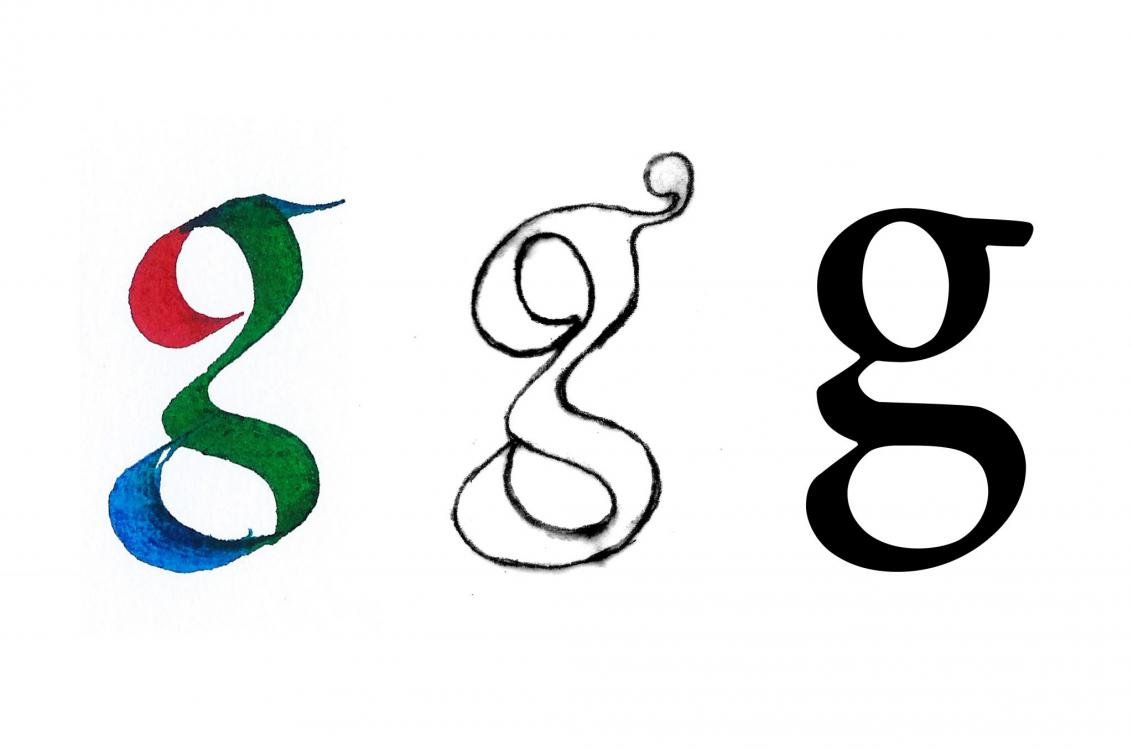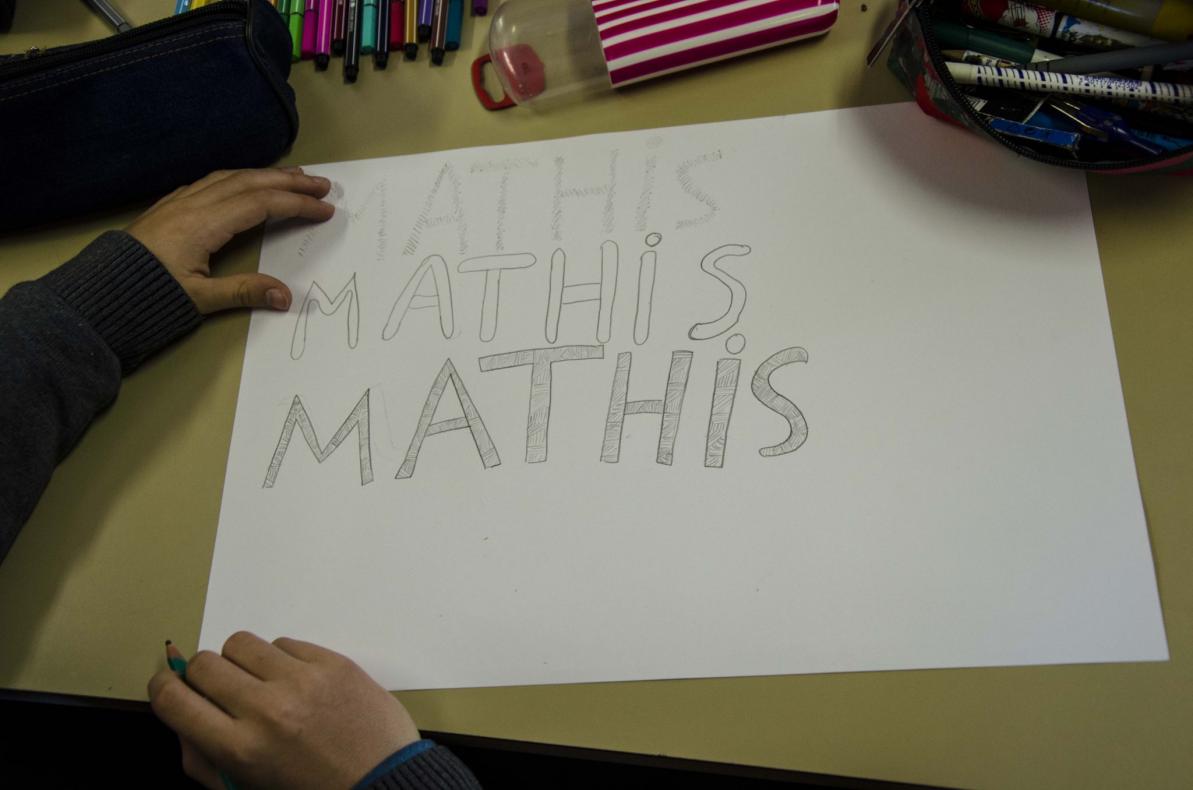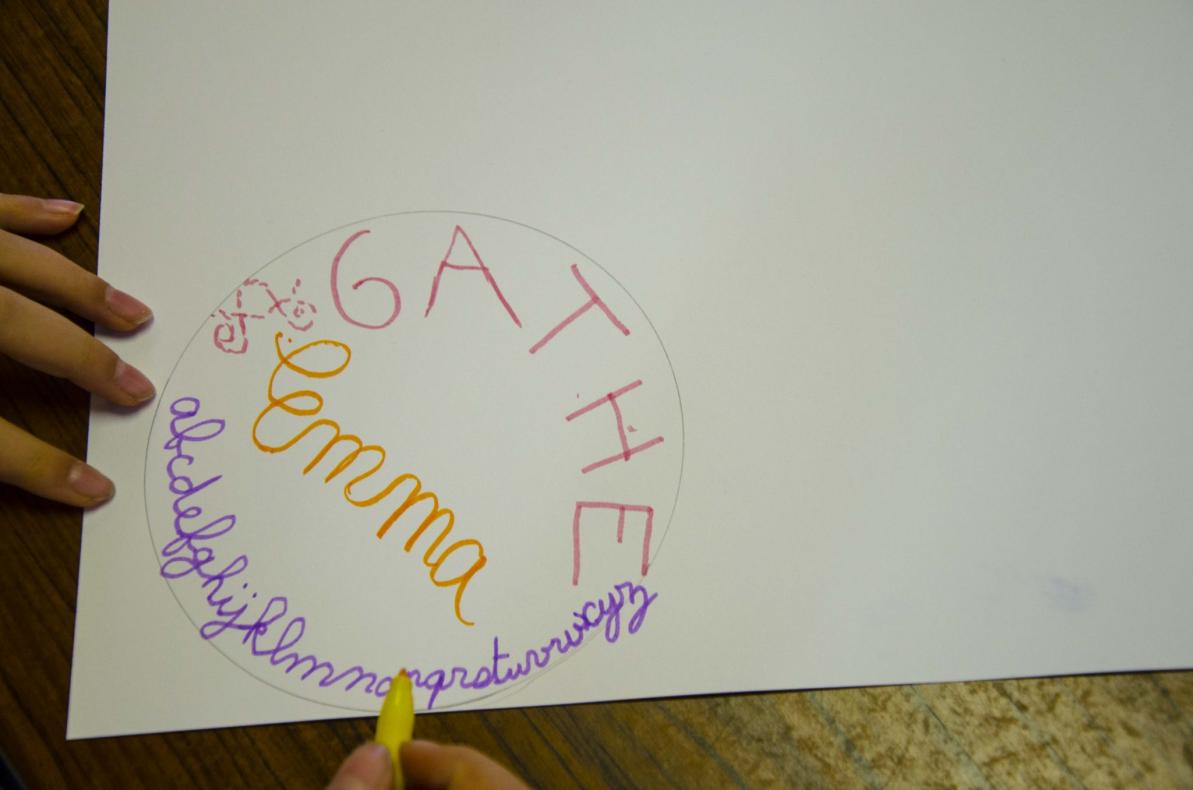
En donnant suite au travail commencé, les élèves sont présentés à trois façons distinctes de produire des lettres.
Lors de ma deuxième intervention à l’École Primaire Publique de Saint-Romain, le 16 février 2017, nous avons donné suite au travail commencé la semaine précédente : la découverte des outils d’écriture déjà disponibles, ainsi que des gestes fondamentaux de la calligraphie, dirigés à la création d’une composition libre contenant une version stylisée de la signature des élèves. Pourtant, entre les deux interventions, en analysant les travaux que les élèves avaient commencé ainsi que les approches en train d’être utilisées, j’ai jugé pertinent de commencer la séance en faisant une présentation et démonstration sur trois façons différentes de produire des lettres et, conséquemment, des textes.
Fred Smeijers, typographe néerlandais contemporain, expose de façon très claire les concepts de calligraphie, lettrage et typographie dans son livre Les Contrepoinçons. Dans ses propres mots (ici traduits par moi-même), la calligraphie n’a lieu que si « l’on fait chaque lettre avec notre main (ou une autre partie du corps) et lorsque chaque partie significative de la lettre est fait d’un seul trait. À partir de la calligraphie, des lettres entières, et même des mots entiers, peuvent être fait d’un seul trait ». Il est important de noter que, dans la calligraphie, la graisse de la lettre est déterminé par l’épaisseur de l’outil utilisé. À son tour, le lettrage comprend « l’usage de lettres dessinées. Ce sont des lettres dont les parties significatives ont été faites d’après plusieurs traits ». En dernier lieu, dans typographie, « la composition du mot, ainsi que la fabrication des lettres, sont déterminées par la machine [en question] ». Il s’agit donc de lettres préfabriquées qui peuvent être mécaniquement combinées à volonté pour composer des textes divers.
Cette résidence a l’enjeu d’éveiller la sensibilité des élèves aux lettres qui nous entourent quotidiennement, afin de les rendre des acteurs conscients et éclairés dans le paysage écrit. Est-ce que des aspects théoriques du dessin de caractères seraient-ils trop hermétiques pour les enfants ? Or, les concepts présentés font déjà partie des connaissances internalisées de façon synthétique par les élèves lorsqu’ils lisent, écrivent ou dessinent des lettres. Cela est démontré par l’échantillon même des travaux démarrés dans le cadre de cette résidence, que j’ai stratégiquement montré lors de la projection pour que les élèves identifient l’approche utilisée en analysant leurs propres travaux. Ainsi, je n’ai pas été surpris par le fait qu’ils ont appris de suite la différence entre ces trois approches de production des lettres, en étant sûr que cette appréhension de leur part nous permettra de transposer notre travail au domaine de la typographie de façon harmonieuse dès que ce moment sera arrivé. Après tout, l’intellectualisation du geste fait partie aussi de son processus de domptage, où la typographie joue un rôle majeur.